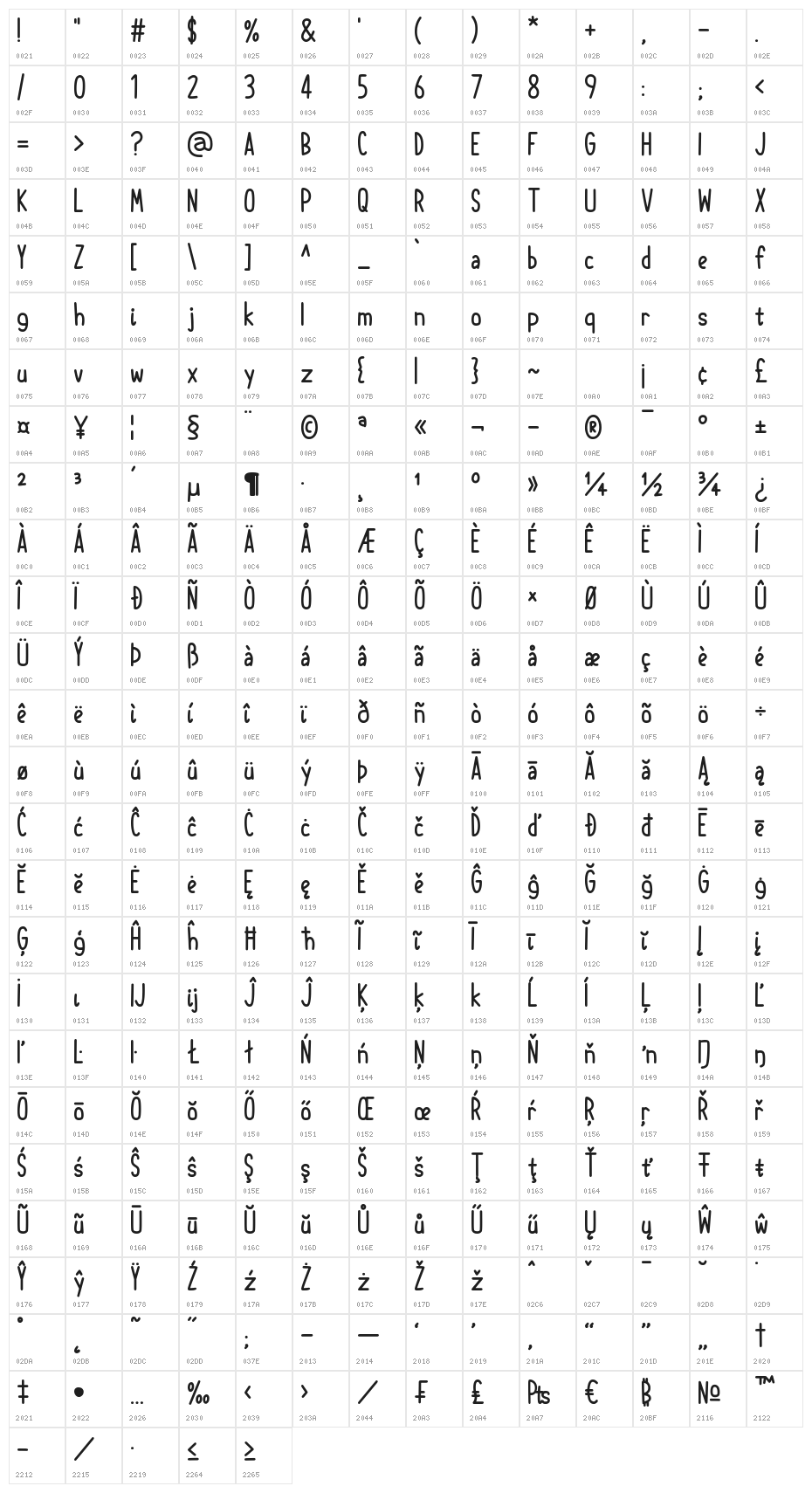
Organic Teabags Font
✎ Handwritten
| 分类 | Handwritten |
| 整体风格 | Casual, Friendly |
| 使用场景 | Headlines, Logos, Invitations |
| 推荐项目 | Ideal for invitations, greeting cards, organic product branding, and eco-friendly designs. |